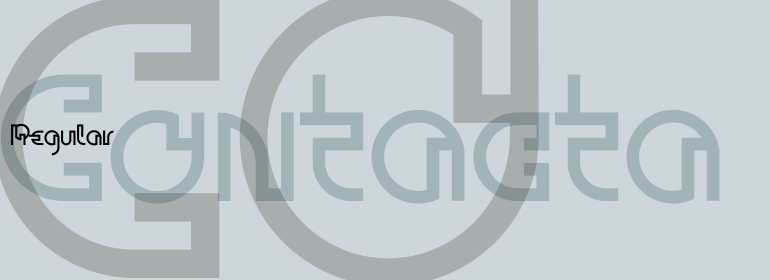
Contacta™
Contacta™,这款字体结构工整、笔画清晰,兼顾美观与易读性,适用于标题、正文、海报、包装、LOGO 等多种场景。字形优雅稳定,风格百搭耐看,适配日常排版与创意设计,让文字呈现更舒适、更具质感。Contacta™一笔一画,皆是细节,以均衡的比例、流畅的线条打造舒适视觉体验,字形端正大气,风格简约现代。无论是商业设计、品牌宣传还是日常排版,都能轻松驾驭,让文字更有格调与力量。Contacta™字体下载。
字体品牌: Linotype(Monotype) 设计师:Weissmantel,Ralf 字体分类:衬线体 字体属性:外文 字符集:Unicode 发布时间: 2018